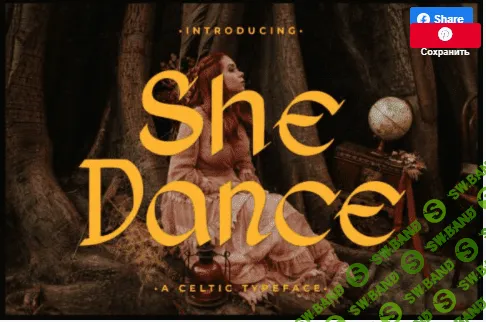
Название: She Dance Font (2021)
She Dance - это шрифт с засечками в кельтском стиле, который прекрасно сочетается с современным стилем! Это отличный выбор для таких проектов, как логотипы, водяные знаки, упаковка продуктов, цитаты и многое другое!